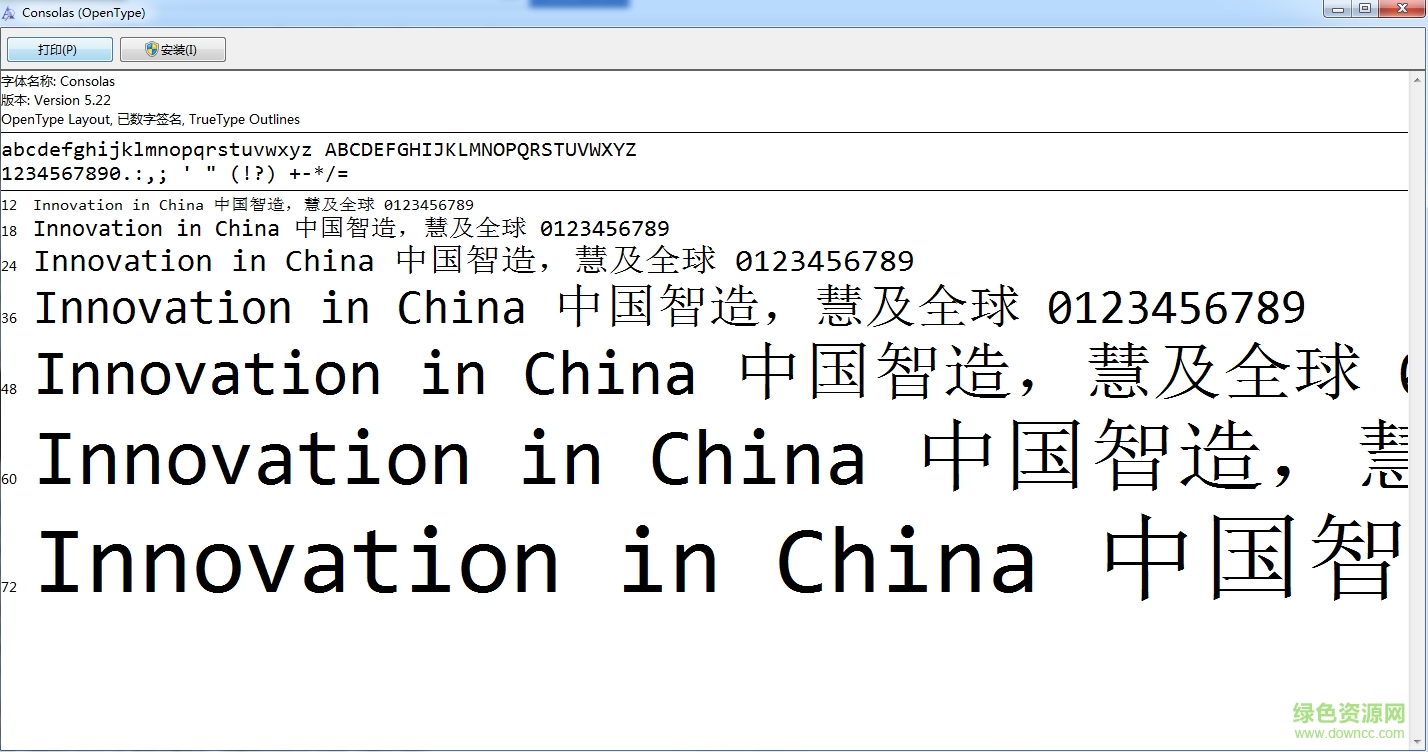
consolas new字體是一款有著固定字符寬度的無襯線字體,邊角柔和,撇捺舒展,辨識度高,常常用作各類顯示器字體,喜歡的朋友快來下載吧!
在一般顯示屏下,用Consolas或Courier New來顯示程序代碼的分別。由于Consolas支持ClearType,所以在LCD顯示屏可以利用次畫素優(yōu)視技術來使字體更清晰。